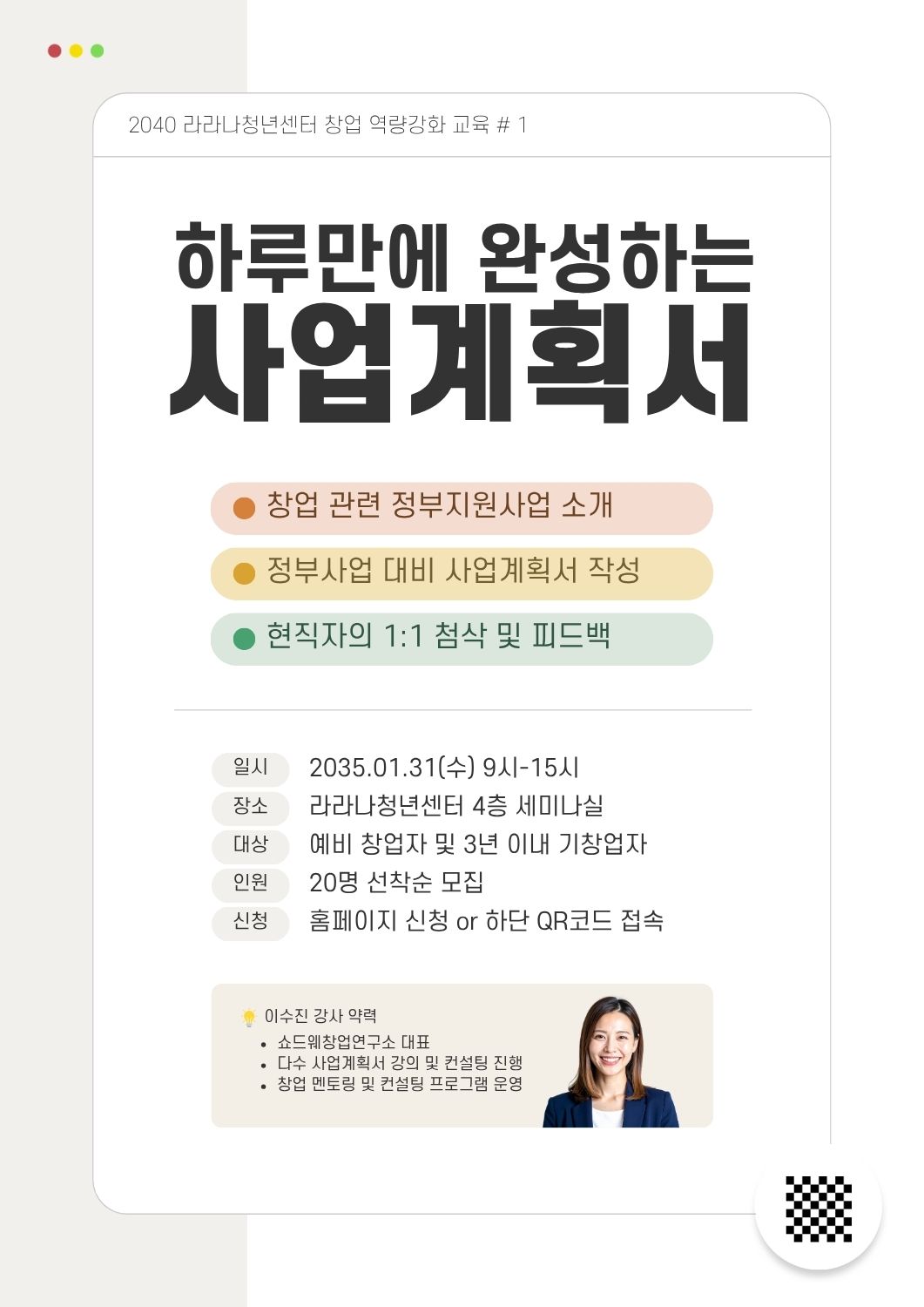
에스코어드림 — S-Core에서 배포하는 무료 폰트입니다. 꽉 찬 직사각형 구조와 수직적인 획 마감이 돋보이는 현대적 고체
에스코어가 나눔의 가치를 실현하고 한글의 아름다움을 공유하기 위해 무료로 배포하는 서체입니다. 이름의 Dream에는 꿈이라는 뜻과 드리다라는 뜻이 함께 담겨 있다고 제작사는 설명합니다.
제작사가 밝힌 조형의 핵심은 세 가지입니다. 꽉 찬 직사각형 구조, 복고적인 형태에 얹은 현대적인 감성, 그리고 각 자소에서 드러나는 수직적인 획의 마감입니다. 마지막 항목이 이 서체의 서명 같은 특징으로, 획 끝을 수평이 아니라 수직 방향으로 정리해 여느 고딕과 다른 표정을 만듭니다. 파일을 재어 보면 받침이 있든 없든 글자 높이가 거의 변하지 않는 네모틀이고, 가로세로 획의 굵기가 고른 민부리 계열입니다.
가장 큰 강점은 굵기 구성입니다. Thin부터 Black까지 아홉 단계로, 무료 한글 서체 가운데 손에 꼽을 만큼 촘촘합니다. 파일 이름이 SCDream1부터 SCDream9까지 숫자로 매겨져 있어 실무에서는 숫자로 부르는 편이 헷갈리지 않습니다. 굵기로 정보의 위계를 여러 겹 나눠야 하는 UI나 인포그래픽에서 특히 힘을 냅니다. 제작사는 이 서체를 제목용으로 규정하고 있지만 실제로는 가벼운 굵기가 본문에도 널리 쓰이는데, 자면을 꽉 채운 구조라 긴 글에서는 글줄 사이를 넉넉히 벌리는 편이 좋습니다.